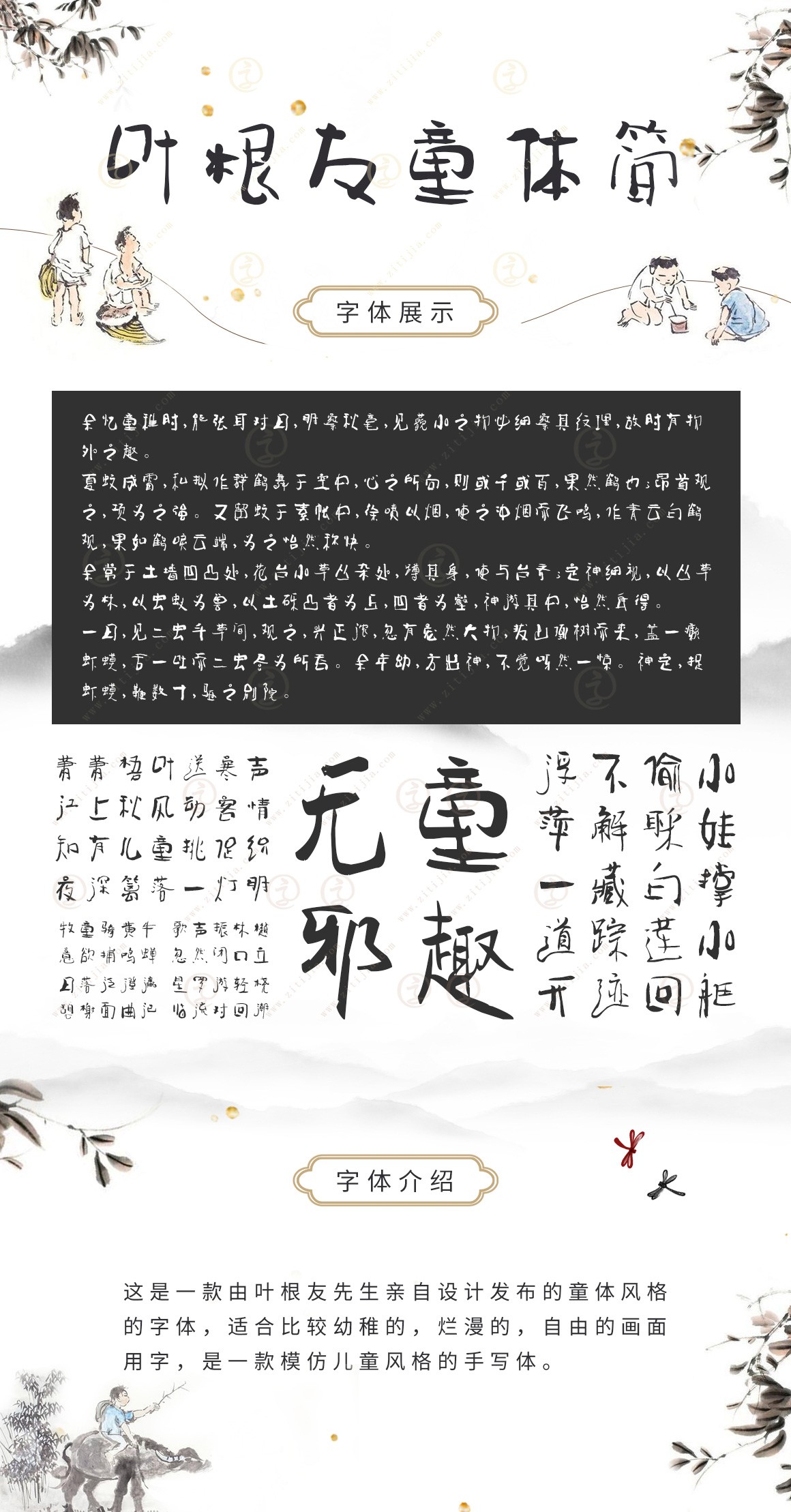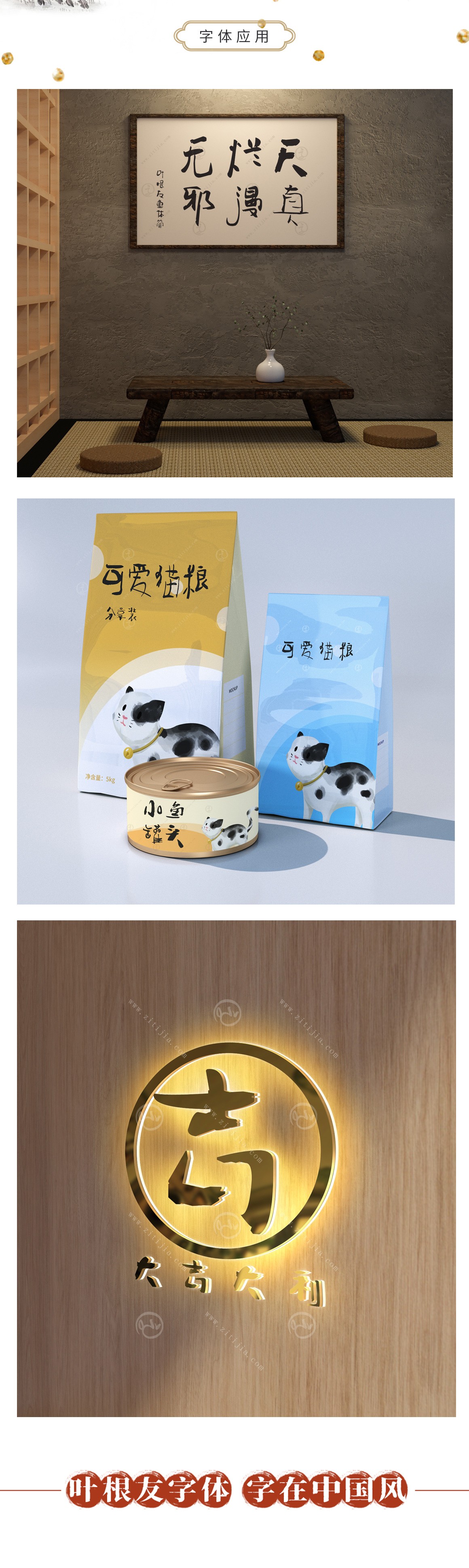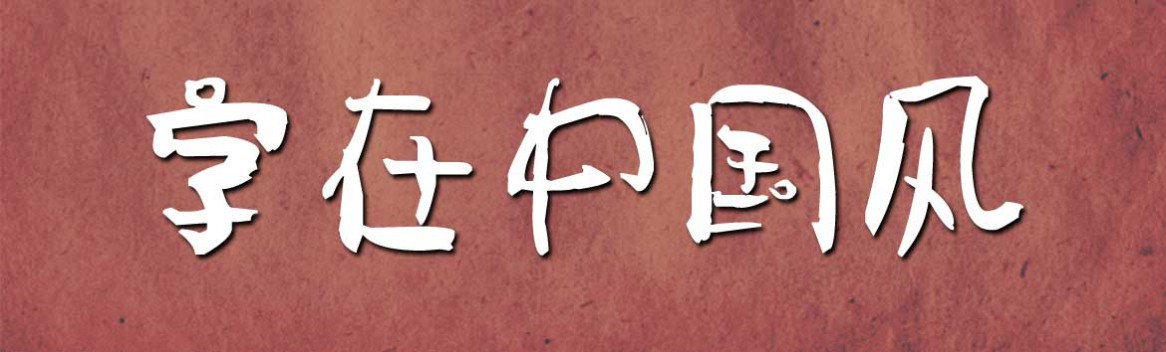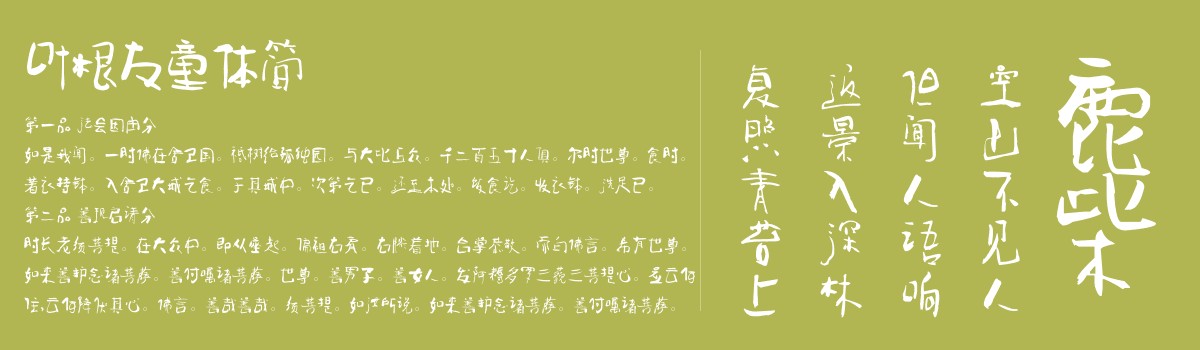
叶根友童体
创作年代:2009年
字体介绍
叶根友童体字体是刻意地去模仿小学生的书写笔法,灵感来自于某次的看到小学生作业本上的一行字,字看上去虽不整齐,但是有书卷气历存其中,叶根友童体在创作中笔画运用大胆,与平时的书写结构完全不同,需要对部首的结体区别于书法的笔法,该字体适合运用于儿童海报和一些轻松自由的主题设计类标题用字。
字体应用